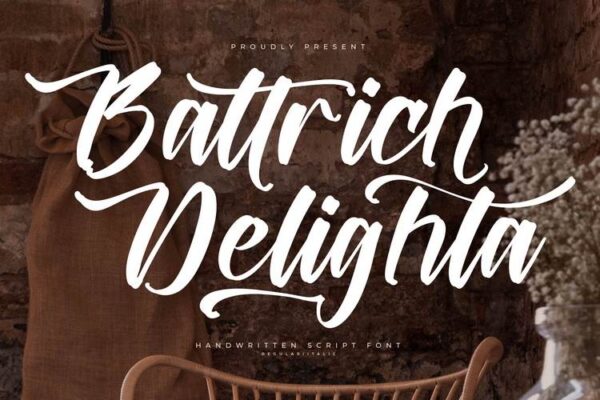
Battrich Delighta ~ Handwritten Script Font
Обзор шрифта: Battrich Delighta ~ Handwritten Script Font
✦ Battrich Delighta – Handwritten Script Font, from Letterena, is a Luxury Script font, suitable for any projects such as: logos, branding projects, homeware designs, product packaging, mugs, quotes, posters, shopping bags, t-shirts, book covers, name card, invitation cards, greeting cards, label, photography, watermark, special events, and all your other luxury and beautiful projects that need a Luxury Script taste.
✦ Рукописный шрифт Battrich Delighta от Letterena – это роскошный шрифт Script, который подходит для любых проектов, таких как: логотипы, брендинговые проекты, дизайн предметов домашнего обихода, упаковки продуктов, кружек, цитат, плакатов, сумок для покупок, футболок, обложек книг, именных карточек, пригласительных билетов, поздравительных открыток, этикеток, фотографии, водяные знаки, специальные мероприятия и все другие Ваши роскошные и красивые проекты, для которых требуется изысканный сценарий.